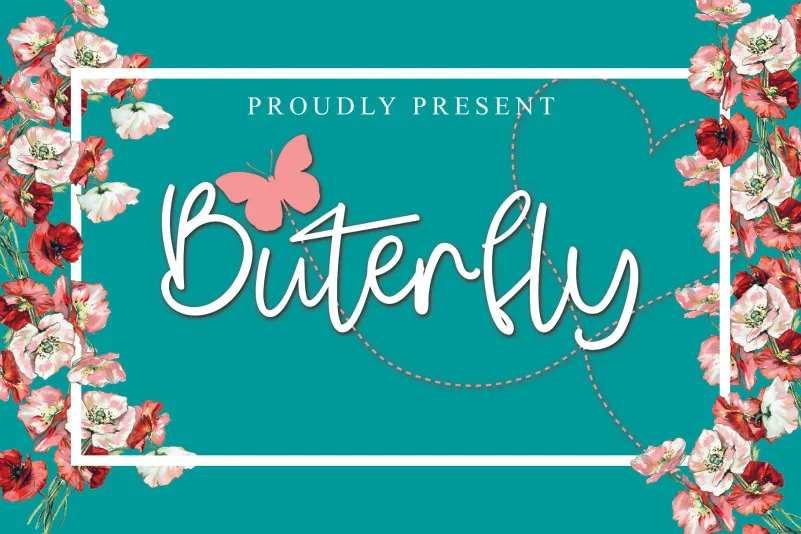
Buterfly Font – Download Grátis
Esta fonte escrita à mão é verdadeiramente única. Cada traço e curve deste design meticulosamente criado se sobressai como uma escolha que certamente tornará qualquer projeto mais único e criativo. Ideal para artistas gráficos, designers de logotipos ou quem está buscando dar um toque distintivo a suas criações digitais, esta fonte oferece um aspecto autêntico e convidativo, onde cada letra parece ter sido escrita por mãos humanas. Possui o potencial de transformar seus projetos em verdadeiras obras de arte, elevando-os ao nível mais alto. Erik Studio traz à vida este design incrivelmente único, uma escolha de fonte que certamente se tornará um queridinho dos criativos. Seja para revolucionar sua identidade visual ou para aperfeiçoar o texto da sua próxima publicação, esta fonte escrita à mão é definitivamente um investimento valioso no seu kit de recursos gráficos.